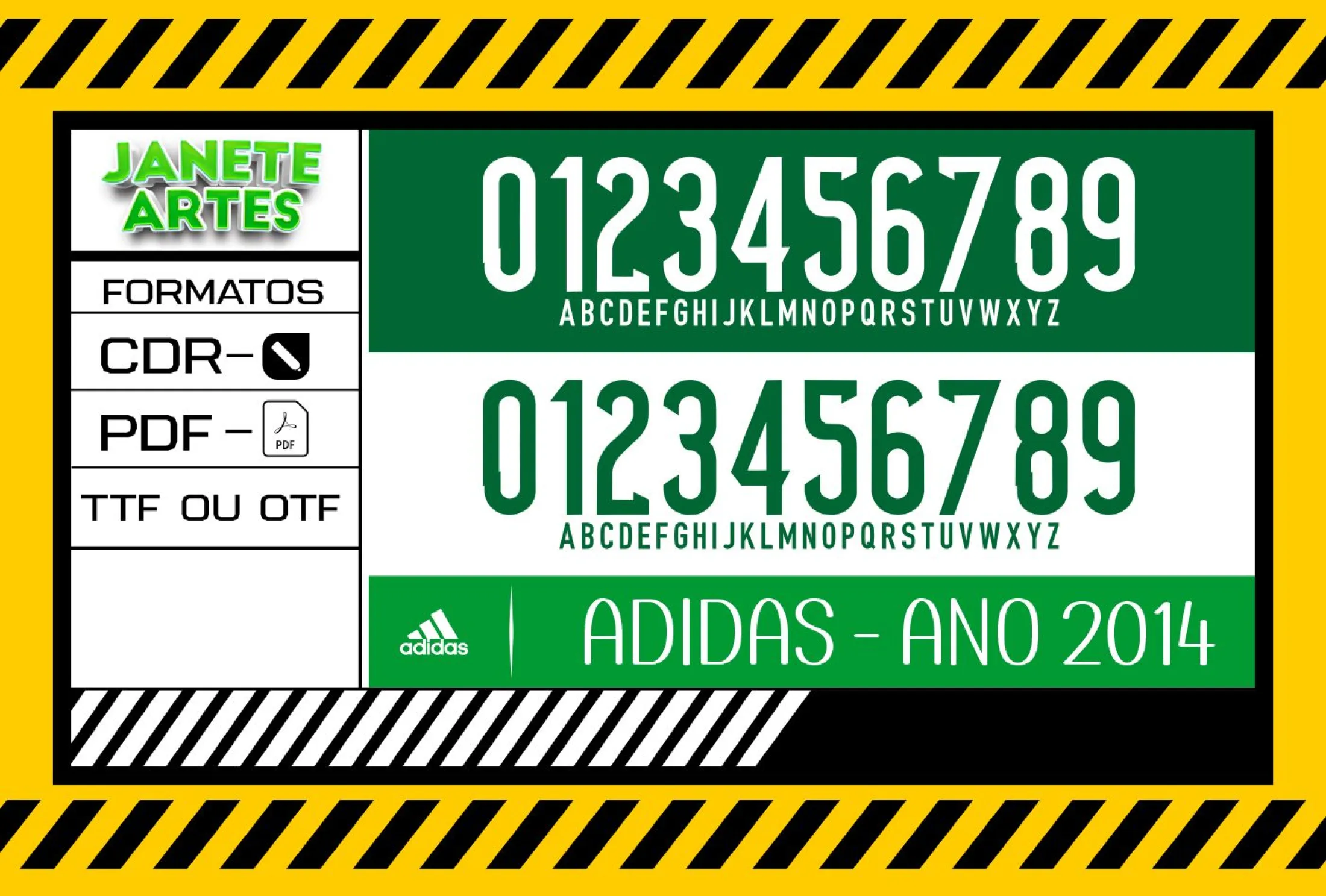
Fonte de Time Tipografia Adidas 2014
Baixe agora o arquivo Fonte de Time Tipografia Adidas 2014 para criar camisetas personalizadas com estilo marcante. Ideal para amantes do esporte e fãs da tipografia exclusiva, fácil de usar e compatível com vários programas.
Uma paixão que virou design
Imagine a emoção de um fã de futebol que queria eternizar a vibe de 2014, com aquele time inesquecível e a tipografia da Adidas que marcou uma geração. Foi assim que surgiu a Arte Fonte de Time Tipografia Adidas 2014 para Camiseta. A inspiração vem dos jogos, das torcidas vibrando e do estilo esportivo com pegada urbana que nunca sai de moda.